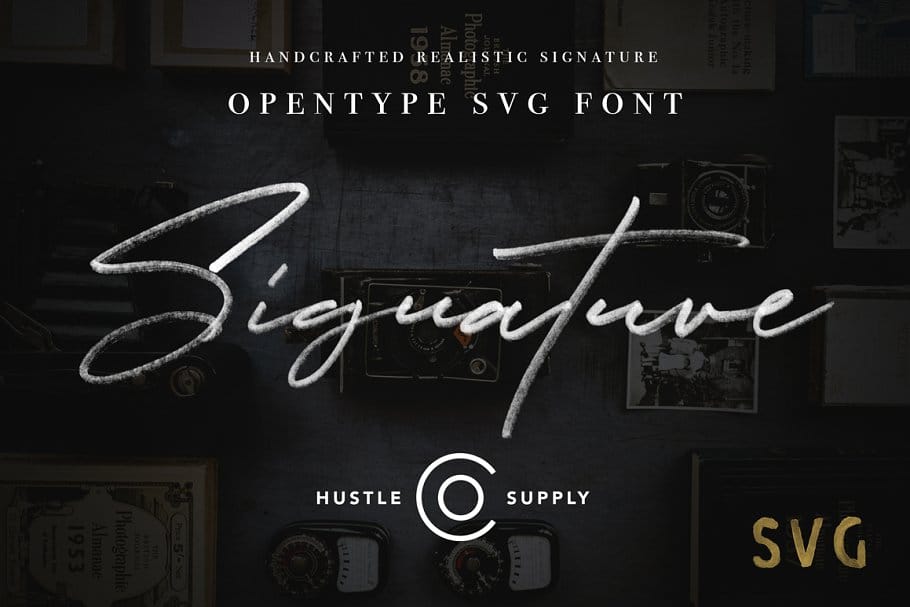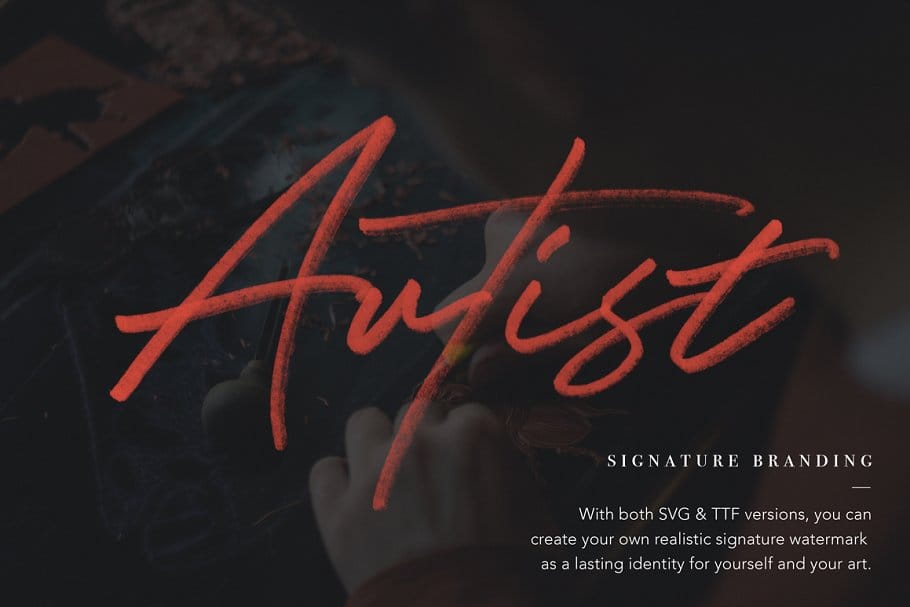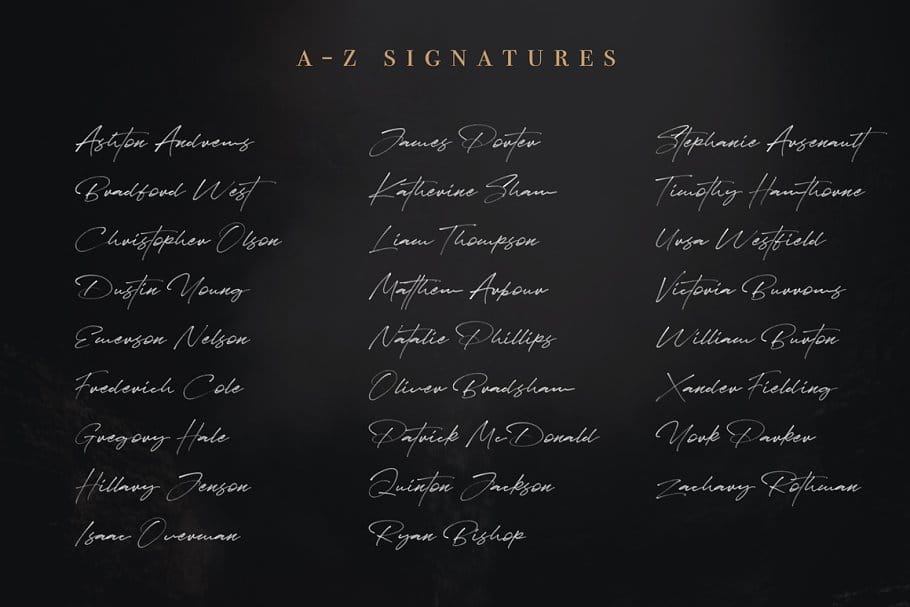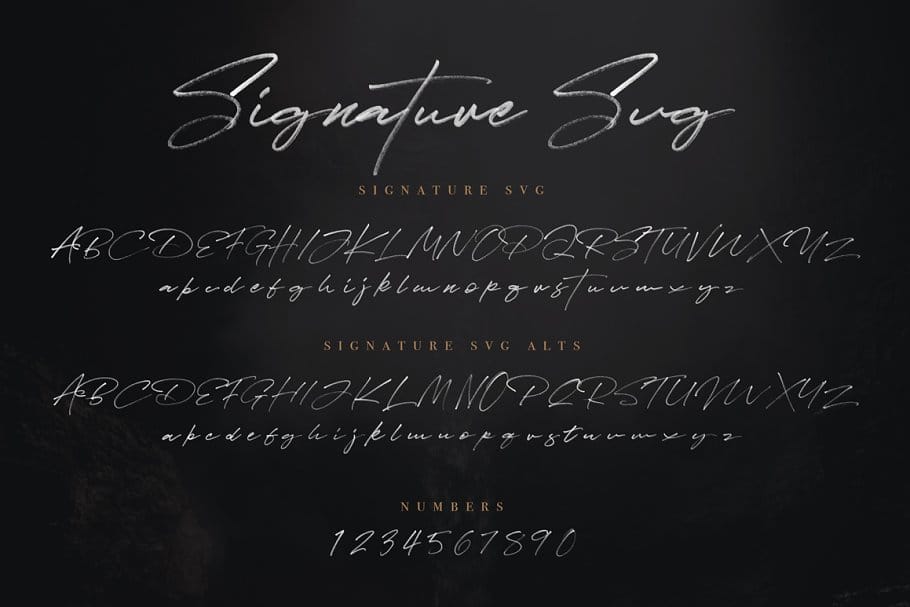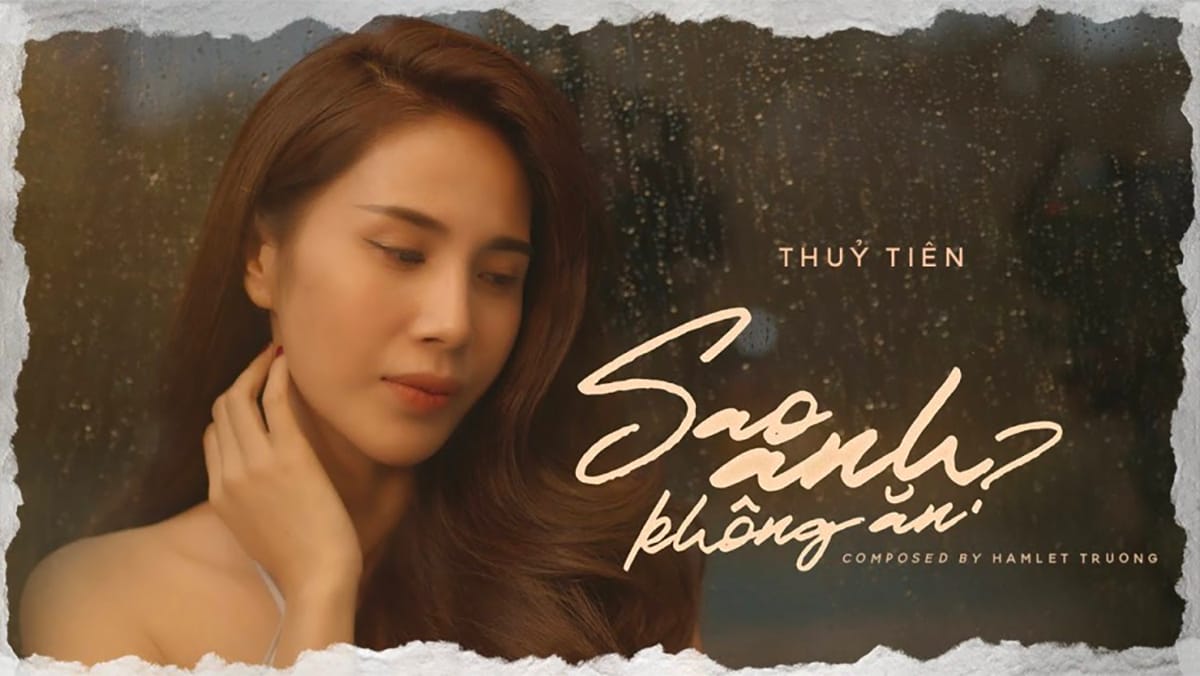
Font JV Signature SVG Full – Font viết tay siêu đẹp
JV Signature SVG Full là font chữ khá đẹp đây là font chữ poster bài hát Sao anh không ăn của ca sĩ Thuỷ Tiên sử dụng.
JV Signature OpenType SVG
Font chữ này không chỉ dành cho chữ ký. Nó sẽ được sử dụng trong nhiều trong các thiết kế khác nhau, từ Tạp chí, Bìa sách, Giới thiệu trên Youtube, Quảng cáo, Tờ rơi, Trang phục, Lời mời đám cưới, v.v.
Font chữ Sao anh không ăn – Thuỷ Tiên sử dụng font chữ JV Signature SVG